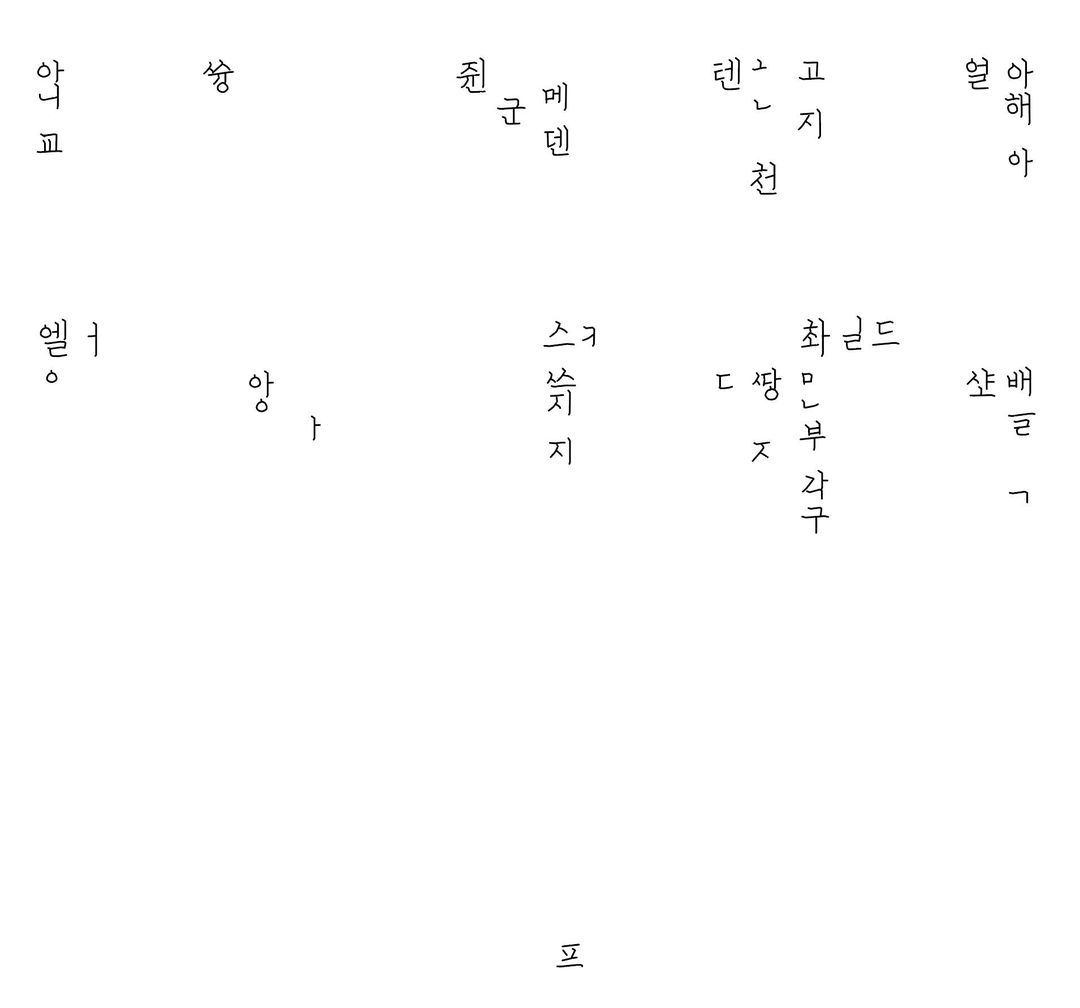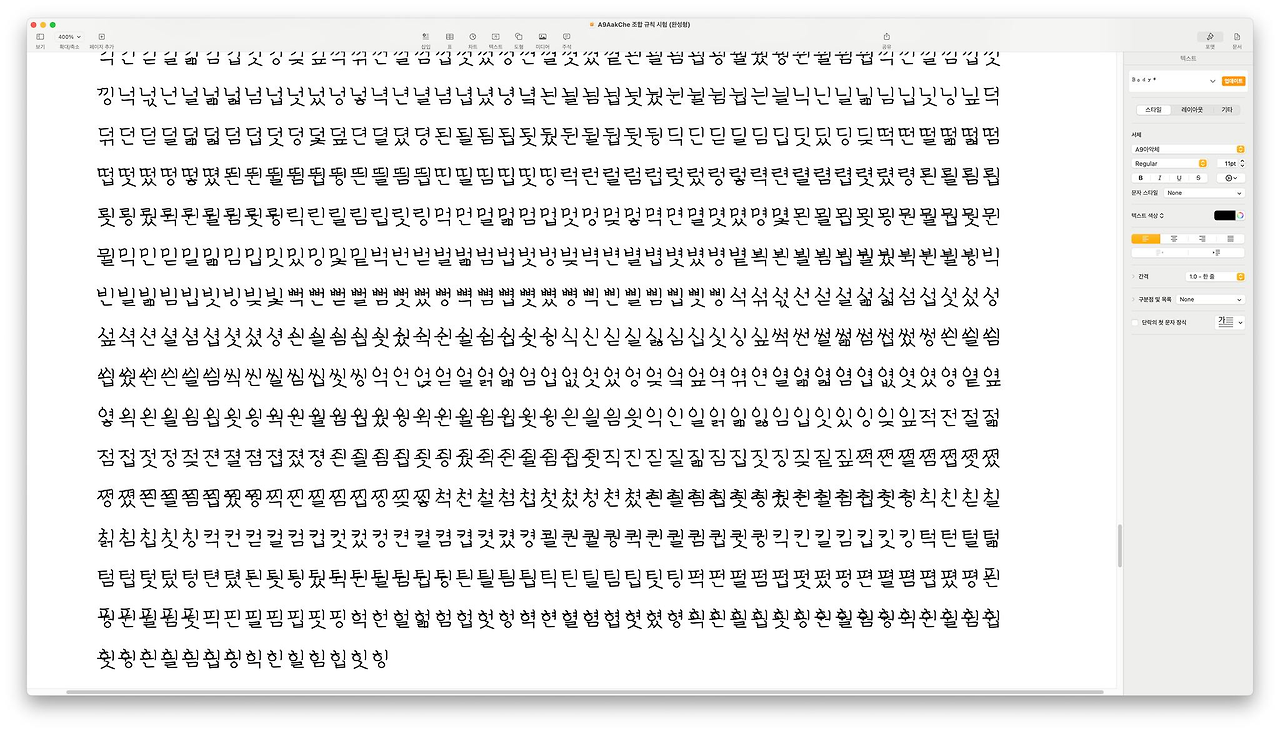
조선시대 영어, 한자, 일본어 교재「아학편」폰트 만들기
다산 정약용의 어린이 학습서에서 글자를 만들어보기
폰트 만드는 것을 셰이프가 아닌 다시 원래 방식인 스트로크 기반으로 다시 돌아왔습니다. 일단 반성문용이라서 ^^
조선시대 영어, 한자, 일본어 교재에서 출판사 굿즈인 폰트 만들기를 해보고 있습니다. 옛한글 소리, 새김이 나오는 사라진 글자들 전부 넣는 중인데 폰트 자리가 없어서 표기하기 힘든 것들이 조금 있었는데 그건 실시간 생성 형태로 만들고
소스가 되는 조선시대 정약용 편찬 한자학습서 「아학편」 에서 한글, 영어, 일본어, 한자를 추출해서 벡터 스트로크를 샘플로 몇개 만들어 초성, 중성, 종성을 만들고 글자를 완성형으로 만들어 봤습니다.
이렇게 적은 글자의 구성으로 한글폰트를 만들었고 영문은 영문 전체, 일본어도 전체가 있어 그대로 그려봤습니다.
다산 정약용이 쓴 글씨(?)를 추출해서 초성, 중성, 종성 및 옛한글 발음 폰트를 구현은 대충해봤습니다. 영문, 숫자, 약물도 만들기는 했는데 온전히 제대로된 글씨체로 적용하려면 일관성이 있는 조형을 유지해야하는데 몇자로만 만드는 것은 한계가 있어 보입니다.
비슷비슷한 손글씨와 차원이 다른 일이 시작됐습니다. 게다가 세로로 글을 썼을 때 균형을 유지하며 만드는 것도 쉽지 않네요... 전용폰트 프로그램으로 폰트메트릭스를 조정해야 하는데 그게 빠르고 쉽게 할 수 있는 일일까 라는 생각을 하게됩니다.
세상에는 너무 다양한 글꼴의 배열이 있기 때문에 일단 하루아침에 이뤄질 일은 아니고 AI보다 사람을 써야 해결될 일이 아닐까 합니다. 다만 고정된 특정영역의 폰트는 무지막지하게 빠른 속도로 만들어 낼 수 있을거예요
더 적은 갯수의 조합으로...